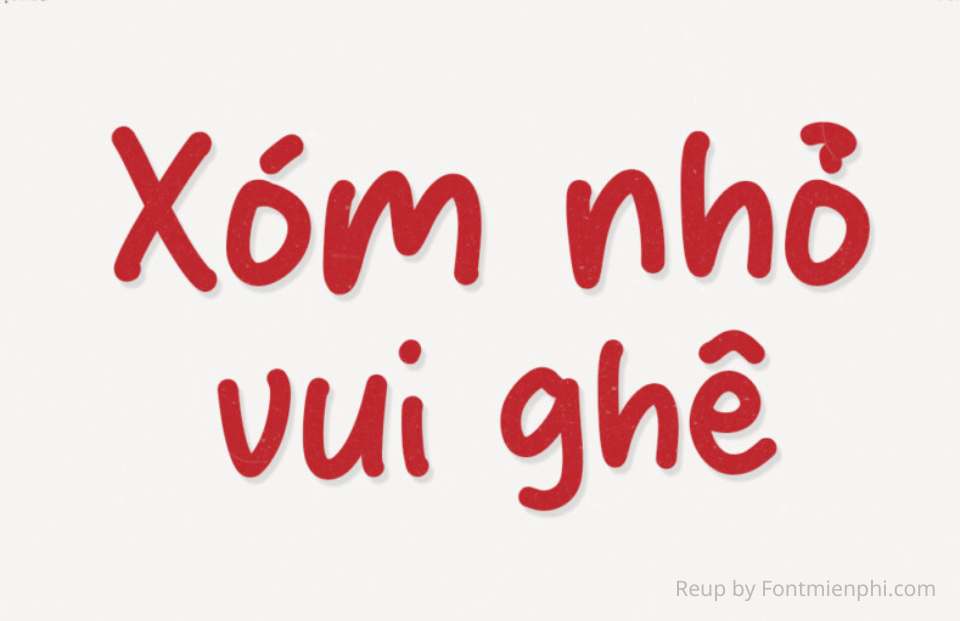
Font Việt Hóa 1FTV VIP Cheese Milky Tuyệt Đẹp Cho Dân Thiết Kế
Bạn đang tìm kiếm một phông chữ ngọt ngào, mềm mại để làm nổi bật các ấn phẩm thiết kế của mình? Font Việt hóa 1FTV VIP Cheese Milky chính là “chân ái” dành cho bạn. Với đường nét tròn trịa, phông chữ này đang tạo nên cơn sốt trong cộng đồng thiết kế dạo gần đây. Hãy cùng tìm hiểu chi tiết về bộ font cực kỳ đáng yêu này nhé!
Giới thiệu về Font 1FTV VIP Cheese Milky
Cheese Milky là một kiểu chữ dạng bong bóng (bubble font) mang phong cách viết tay vô cùng tự nhiên và ngộ nghĩnh. Đúng như tên gọi “Cheese Milky” (Sữa phô mai), phông chữ này mang lại cảm giác ngọt ngào, béo ngậy và cực kỳ thu hút ánh nhìn.
Nhờ đội ngũ 1FTV, bộ font này đã được Việt hóa 100%, khắc phục hoàn toàn tình trạng lỗi dấu khi gõ tiếng Việt, giúp các designer Việt Nam dễ dàng sử dụng trên mọi nền tảng phần mềm như Photoshop, Illustrator hay Canva.
Điểm Nổi Bật Của Font Cheese Milky Việt Hóa
1. Phong cách thiết kế siêu “Cute”
Các nét chữ của Font Việt hóa 1FTV VIP Cheese Milky được bo tròn khéo léo, nét thanh nét đậm hài hòa. Phông chữ không quá cứng nhắc mà mang lại sự linh hoạt, vui tươi, cực kỳ phù hợp với các dự án hướng tới giới trẻ và trẻ em.
2. Tối ưu hóa dấu Tiếng Việt chuẩn xác
Dấu câu (hỏi, ngã, nặng…) được nhóm tác giả chăm chút tỉ mỉ, đặt đúng vị trí và giữ nguyên được “vibe” dễ thương của font gốc. Nhờ đó, tính thẩm mỹ của đoạn text luôn được đảm bảo ở mức cao nhất.
Ứng Dụng Thực Tế Của Phông Chữ Cheese Milky
Với sự đa dụng của mình, font Cheese Milky Việt hóa là lựa chọn hàng đầu cho các hạng mục thiết kế:
• Thiết kế bao bì: Vỏ hộp bánh kẹo, tem nhãn trà sữa, đồ ăn vặt.
• Truyền thông Mạng xã hội: Làm typography cho các bài đăng Instagram, thumbnail YouTube, TikTok mang phong cách trẻ trung.
• Ấn phẩm thiếu nhi: Bìa sách, truyện tranh, poster sự kiện cho bé.